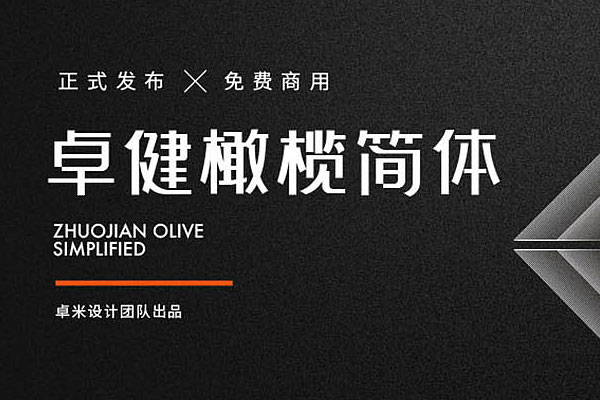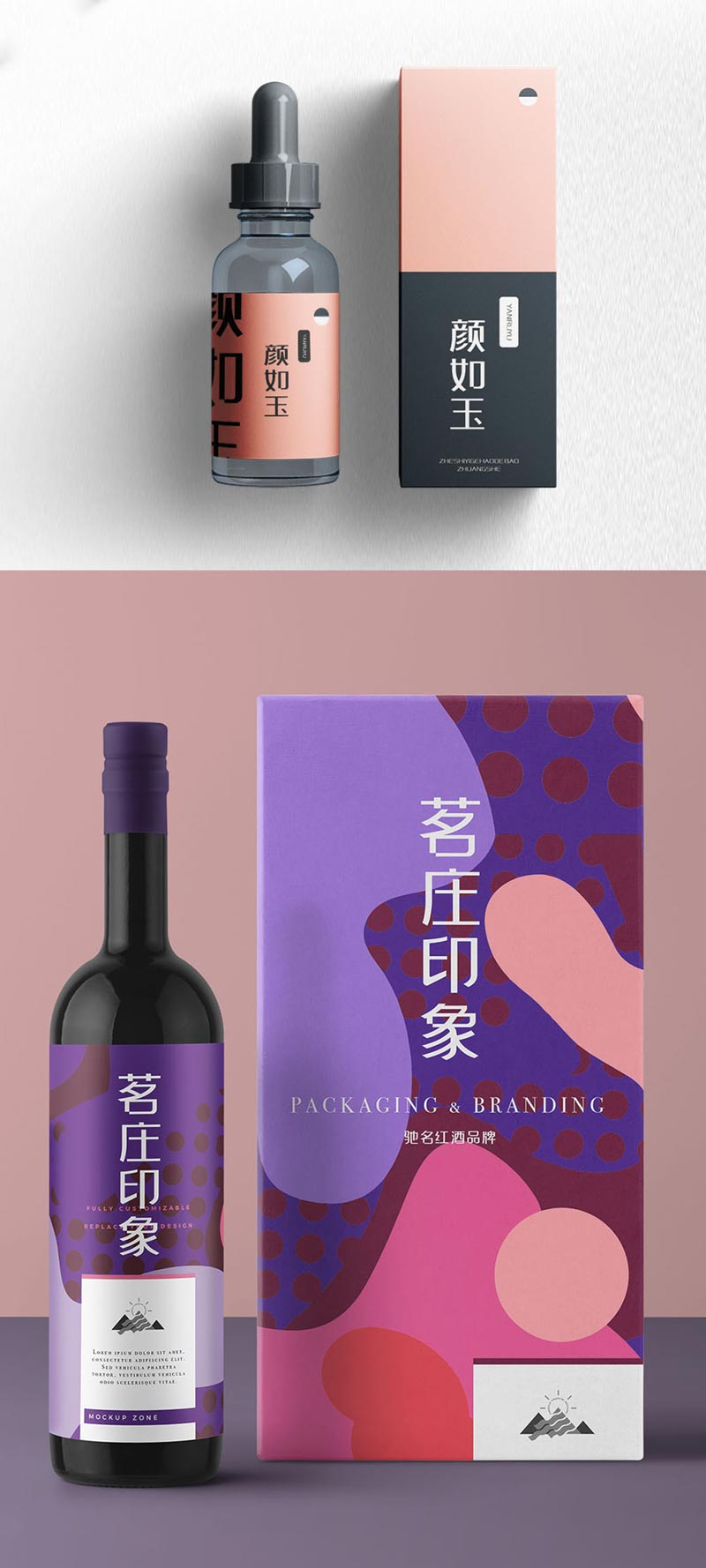
卓健橄榄简体
在2019年双11购物节,卓米设计团队默默为设计师们准备了一份厚礼——免费商用的中文字体卓健橄榄简体。在2018年初,卓米设计部平面小组就开始了公司首套字库的设计之旅,历时一年,于2019年初完成了这套初肯字库的设计,总计7050个中文汉字,52个英文字母,139个阿拉伯数字及常用标点符号。
从细致入微的调研,到精准的定位,再到精细的草图设计、规范制定,最后到成功的成稿,这个过程中,他们团队经历了无数的困难与磨合。而今天,这套卓健橄榄简体终于面世了。更重要的是,它是免费商用!免费商用!免费商用!
卓健橄榄简体是一款充满现代感的字体,部分笔画的斜切处理赋予了字体更强的设计感和时尚属性。整体字身稍偏上,更符合现代审美。圆角的设计让整个字体看起来更加圆润,富有趣味性。口字结构中左下角留白,这种个性化处理方式使字体更具特色。32度的斜切处理,使字体更加设计感十足,更显时尚。
卓健橄榄简体适用于多个行业,包括医疗、互联网、时尚等。无论是你正在为下一个创意项目寻找合适的字体,还是正在寻找一款可以定制化的品牌字体,卓健橄榄简体都是一个值得考虑的选择。让我们一起期待卓米设计团队未来会为我们带来更多优秀的免费商用字体!